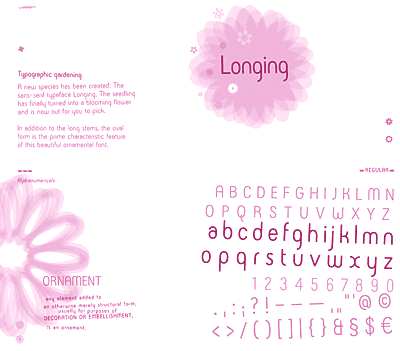
Blumig frisch und leicht präsentieren sich die Schriftgewächse des Düsseldorfer Schriftlabels Font-o-Rama. Nina David gestaltet seit sechs Jahren Schriften. Diese bietet sie seit drei Jahren als "junge Freefonts zum selber pflücken" im Internet an. Nun wurde das Sortiment erweitert – vier ausgewachsene Zuchterfolge stehen zum Verkauf bereit.